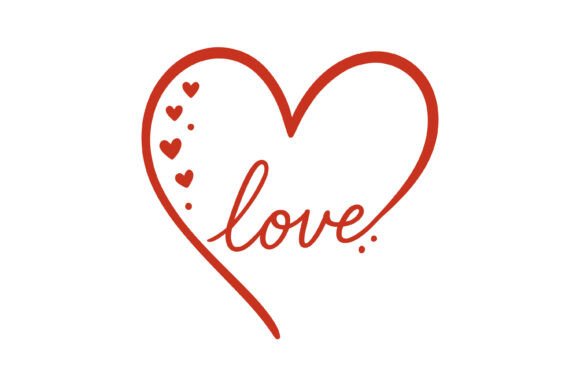
Handwritten Love Heart Outline
์ •๋ฐ€ํ•˜๊ฒŒ ์ œ์ž‘๋œ Handwritten Love Heart Outline๋Š” ๊น”๋”ํ•œ ๋ฒกํ„ฐ, ๋ถ€๋“œ๋Ÿฌ์šด ํƒ€์ดํฌ๊ทธ๋ž˜ํ”ผ ๋ฐ ์•ˆ์‹ฌํ•  ์ˆ˜ ์žˆ๋Š” ์ƒ์—…์šฉ ๋ผ์ด์„ ์Šค๋ฅผ ์ œ๊ณตํ•ฉ๋‹ˆ๋‹ค.